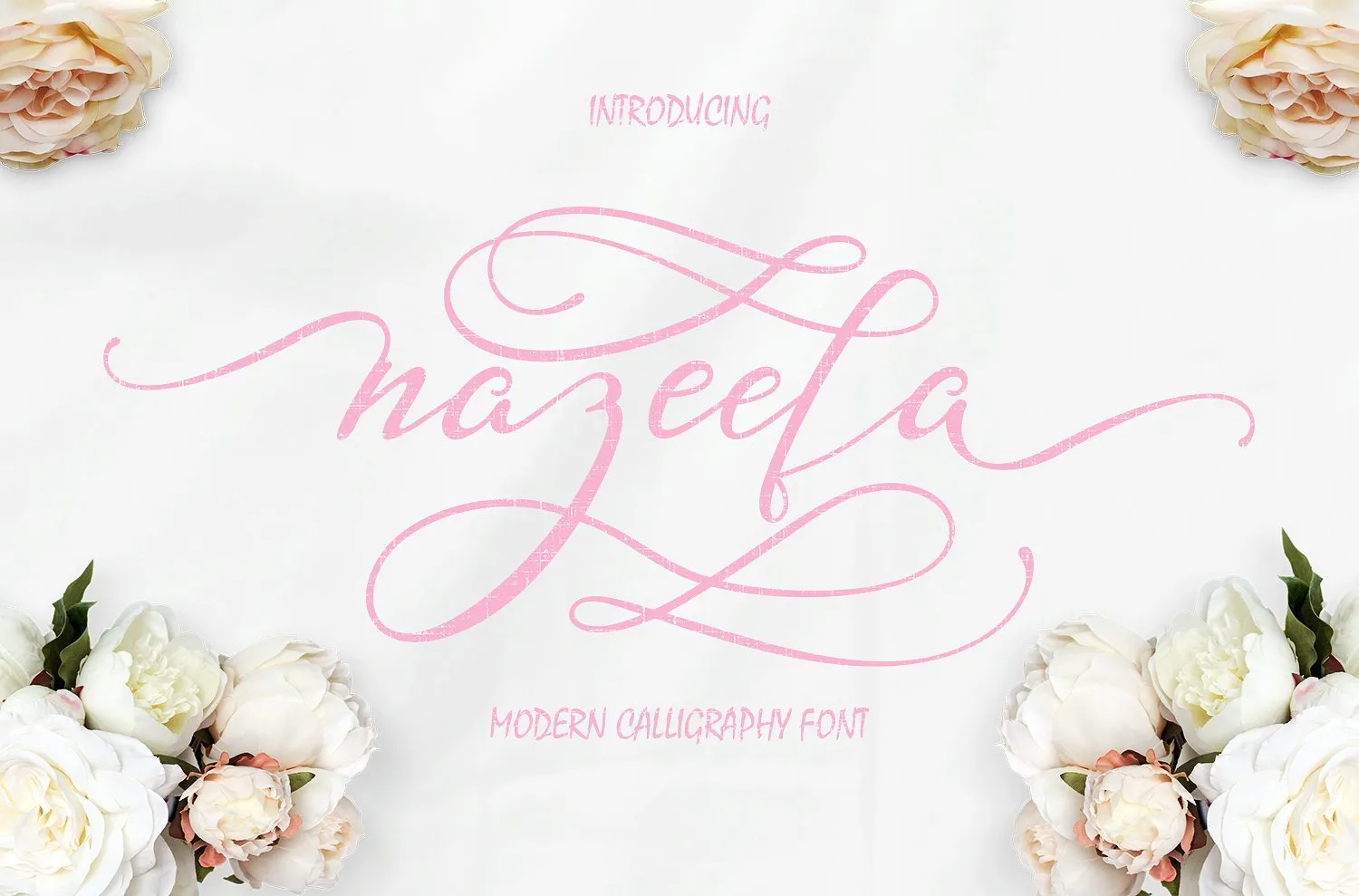
Nazeefa Script Font – Download Grátis
A fonte Nazeefa Script é uma obra-prima da arte da tipografia moderna criada pelo designer Hamilton. Esta fonte handwritten possui um conjunto variado de estilos e características únicas, tornando-a ideal para projetos femininos, moda, eventos de casamento e convites de casamento. A Nazeefa traz aos designers uma extensa gama de possibilidades, tornando-a a escolha perfeita quando você busca personalizar qualquer tipo de projeto. Com seu charme handwritten moderno, a Nazeefa é certamente um atalho para criar designs incríveis e únicos.